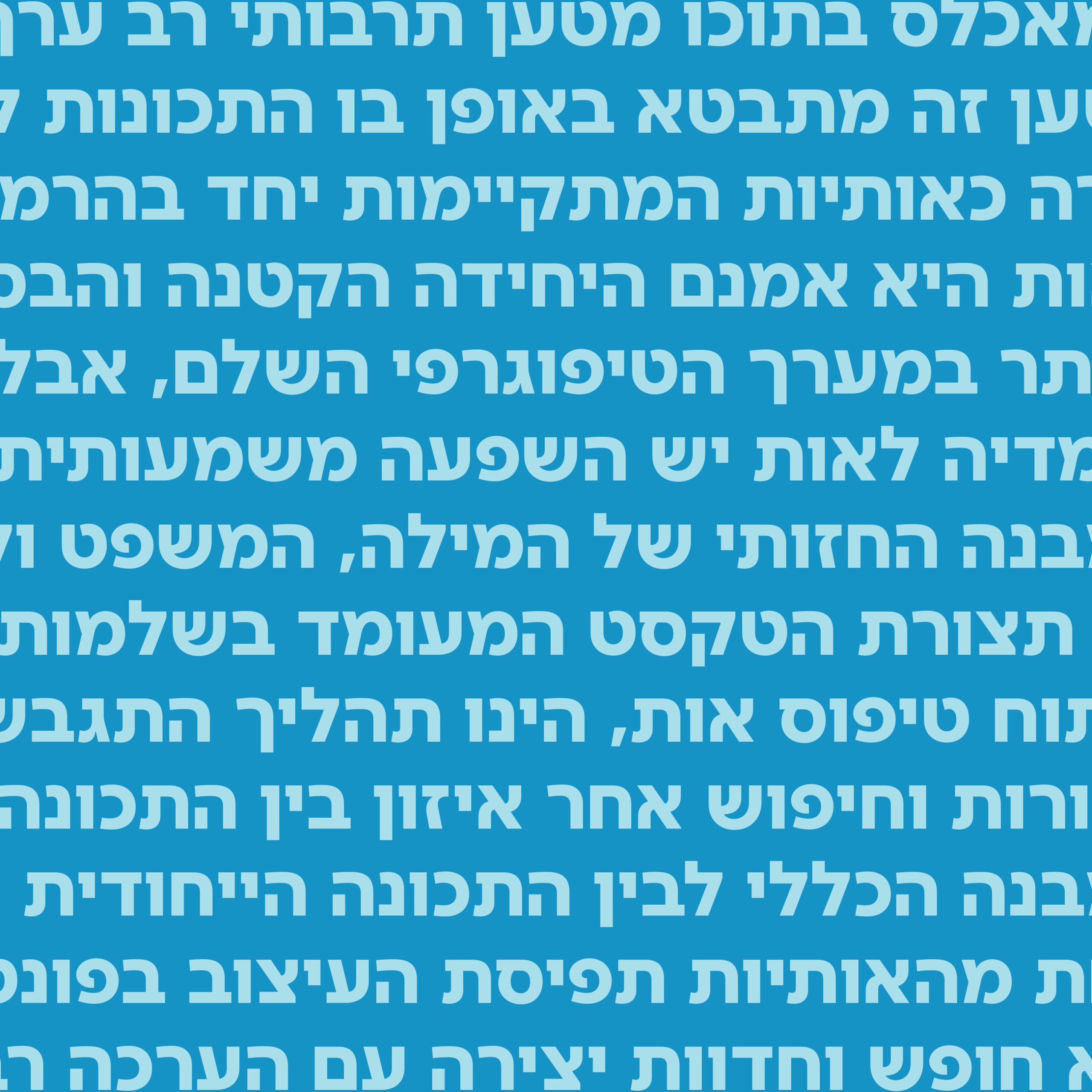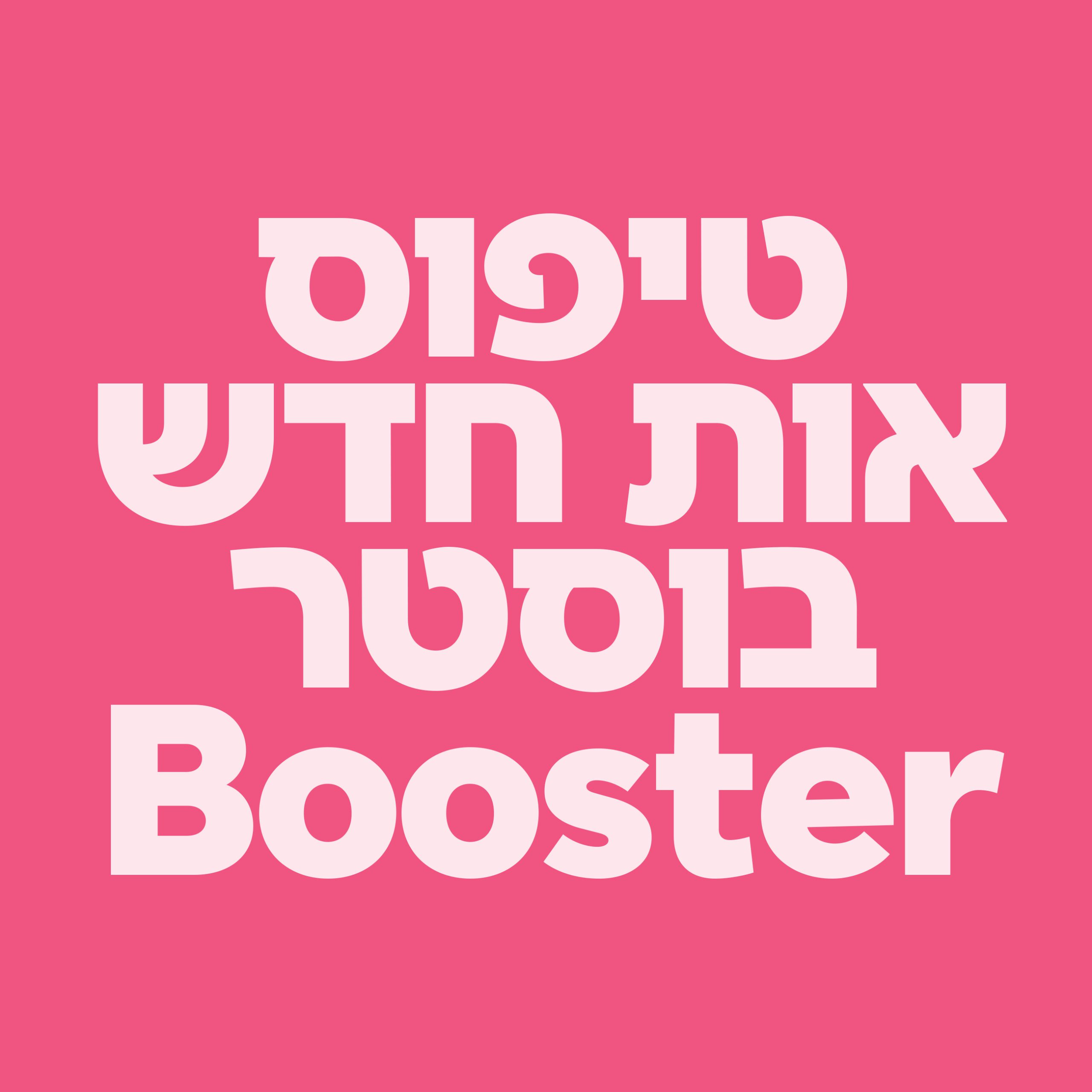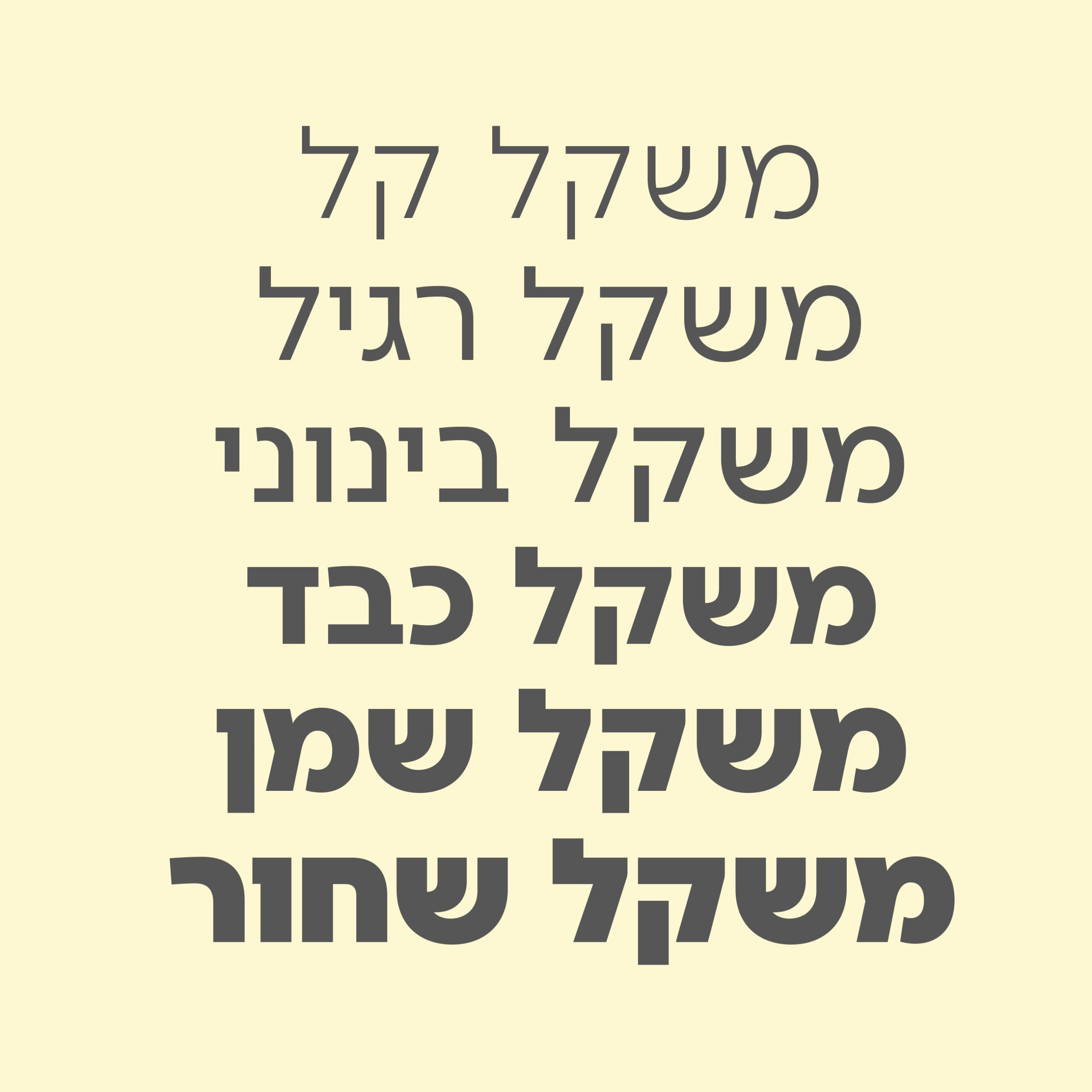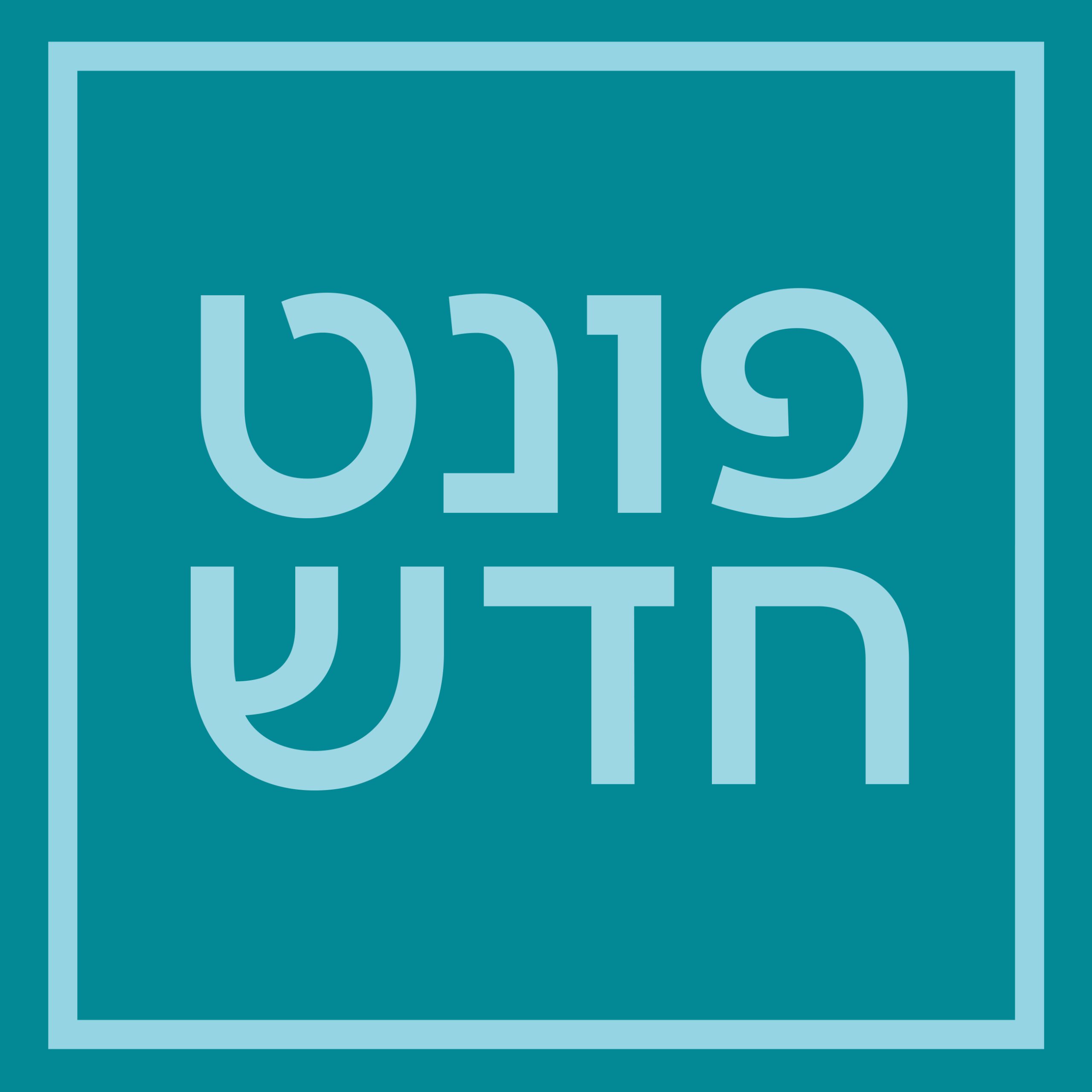
בוסטר / Booster
בוסטר Booster מגיע עם עשרות שפות תואמות ובמשקל VF החדש
• שם הגופן:בוסטר
• מעצב הגופן:נדב עזרא
• סגנון:סאן סריף
• קטגוריה: גופני VF עברית חדשים טקסט ראווה דו-לשוני
• מאפיינים: קל רגיל בינוני כבד שמן שחור
סיפור הגופן:
אות טקסט סאן סריפית עברית ולועזית אשר בנויה מקו אופטי אחיד, ויוצקת את תכונות האותיות העבריות על גריד גאומטרי פשוט: ריבוע, עיגול ומשולש. הסגנון הגאומטרי משווה לאות מראה גרפי בסיסי ועגלגל לצד קריאות זורמת ונעימה. אות זו נבנתה תוך שמירה מוקפדת על שקיפות ואוניברסליות כך שתפנה את כל הבמה עבור העיצובים שלכם. בשל פשטות המבנה טיפוס אות זה מתאים מאוד למסכים.